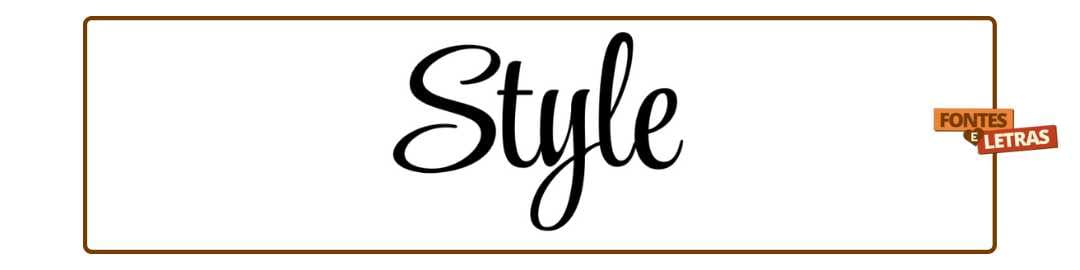
As letras cursivas e itálicas são estilos de texto em Unicode com traço inclinado e elegante, prontos para copiar e colar na bio, no nome, em frases e em qualquer app — sem instalar fonte nenhuma. Escreva o seu texto na caixa lá em cima e escolha entre vários estilos de cursiva e itálico.
As letras cursivas são caracteres Unicode com um traço inclinado e fluido que imita a escrita à mão. Diferente de uma fonte que você instala, elas viajam junto com o texto, então aparecem cursivas em qualquer lugar onde você colar — celular, PC, redes sociais.
💡 Dica: as cursivas mais "clean" (itálico fino) funcionam em mais apps. As muito enfeitadas às vezes o app não mostra.
Tem letra cursiva pra todo gosto, da mais elegante à mais estilosa. Escreva o seu texto pra ver todas, mas aqui vão os favoritos:
| Estilo | Exemplo | Combina com |
|---|---|---|
| Cursiva | 𝓵𝓮𝓽𝓻𝓪𝓼 𝓬𝓾𝓻𝓼𝓲𝓿𝓪𝓼 | nome, frases fofas |
| Cursiva negrito | 𝓵𝓮𝓽𝓻𝓪𝓼 𝓫𝓸𝓵𝓭 | destaques na bio |
| Itálico | 𝘭𝘦𝘵𝘳𝘢𝘴 𝘪𝘵á𝘭𝘪𝘤𝘢𝘴 | legendas elegantes |
| Itálico negrito | 𝙡𝙚𝙩𝙧𝙖𝙨 𝙗𝙤𝙡𝙙 | títulos com força |
| Serif cursivo | 𝑒𝓁𝑒𝑔𝒶𝓃𝓉𝑒 | tatuagem, frases |
A cursiva imita a escrita à mão, com traços mais fluidos e enfeitados. O itálico é a letra normal inclinada para a direita. As duas ficam elegantes — é questão de gosto.
Sim, na bio, no nome, nas legendas e nos stories. São caracteres Unicode, o estilo é mantido ao colar.